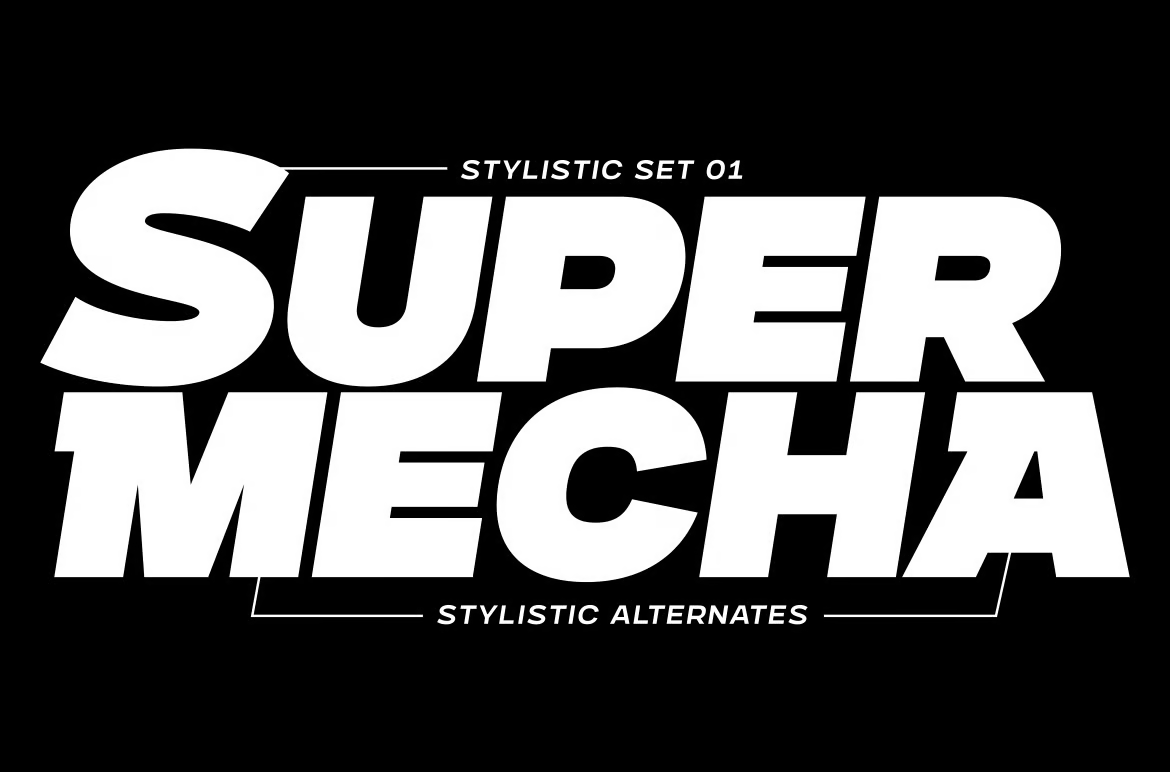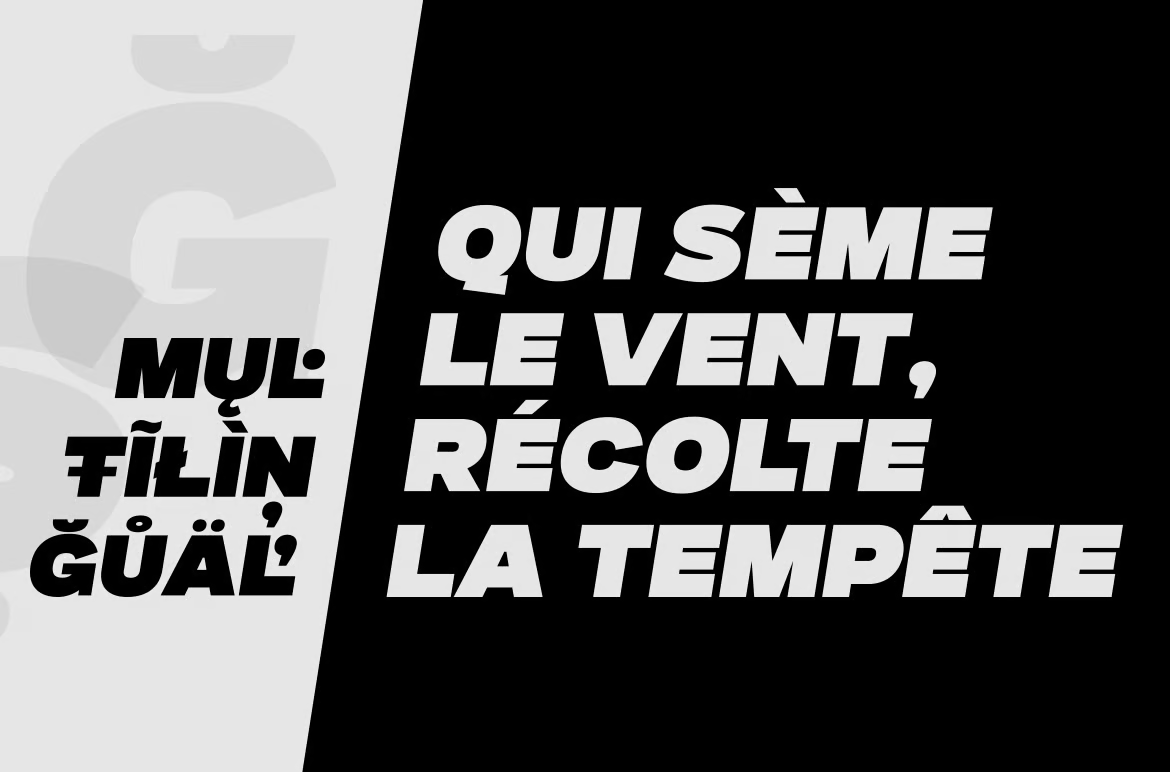
Gunterz Font
Description de Gunterz Font
Gunterz est une police puissante qui prend en charge toutes les lettres majuscules et l’utilisation du sans-serif fera ressortir votre déclaration. C’est le meilleur moyen d’augmenter la valeur que vos projets apportent.
Gunterz est disponible en quatre graisses avec des polices italiques similaires aux graisses normales. Il possède des fonctionnalités OpenType telles que des alternatives stylistiques et des ensembles stylistiques pour lui donner une forme d’élégance. De plus, Gunterz prend en charge les caractères cyrilliques et peut donc être utilisé sur différentes plates-formes.
Utilisations idéales :
Titres des affiches
Conception d’emballage
Titres
Logotypes
Graphiques animés
Titres de films
Promotions sportives
Thèmes technologiques futuristes